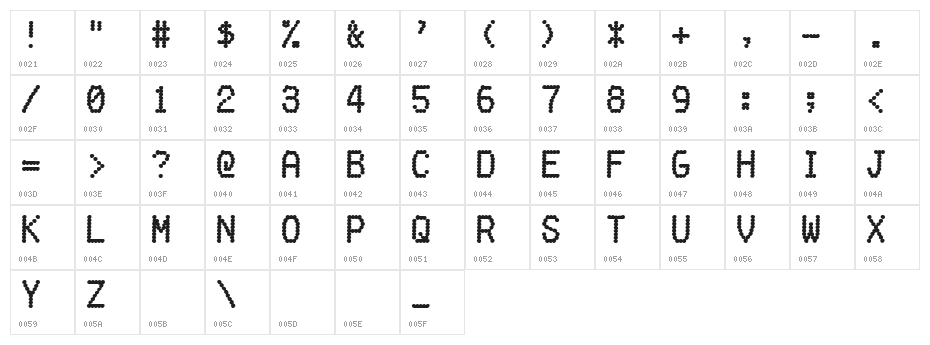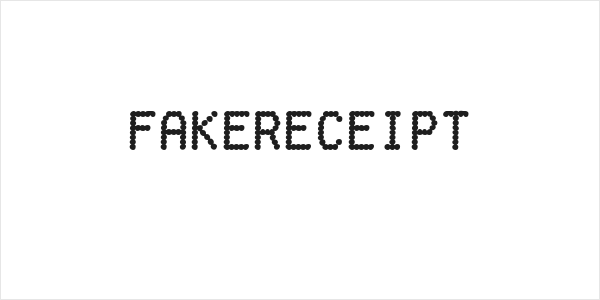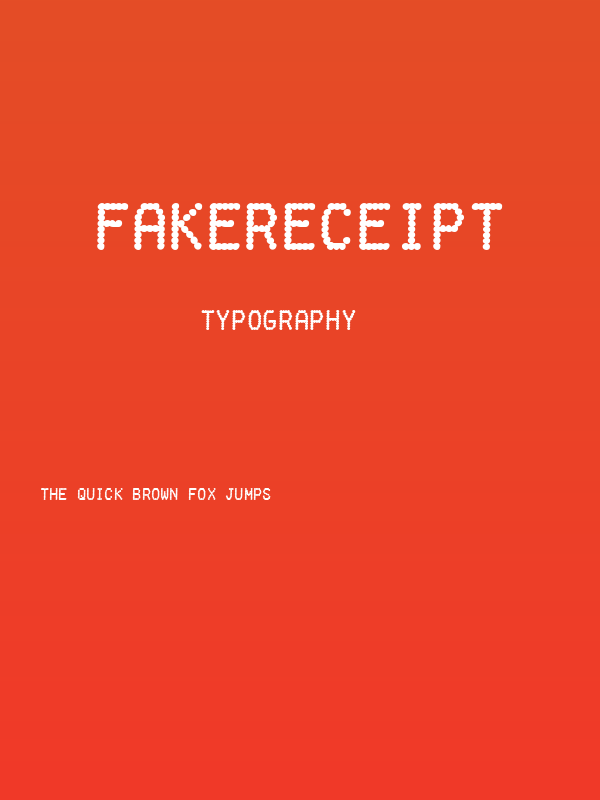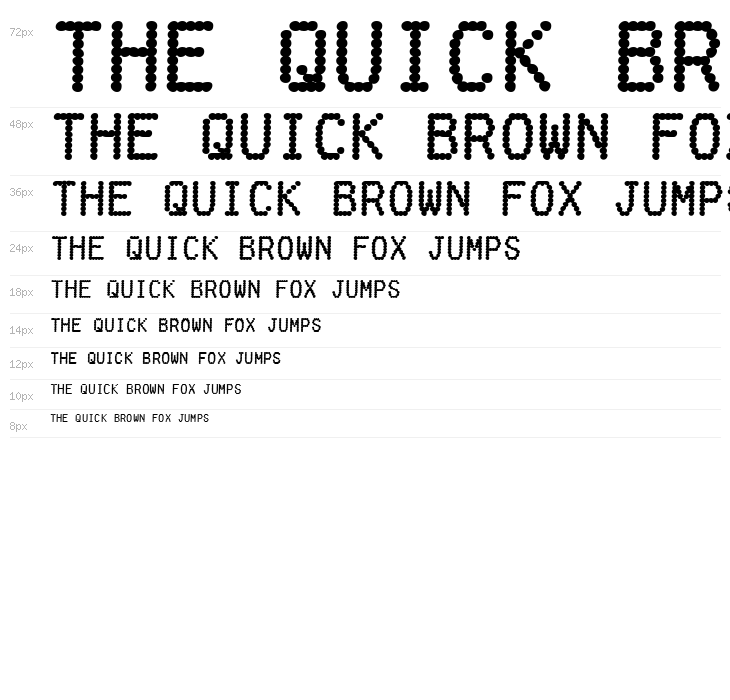
FakeReceipt Font
| Gesamtstil | Retro, Modern |
| Anwendungsfall | Logos, Posters, Digital Art |
| Vorgeschlagene Projekte | Ideal for retro-themed designs, tech-related branding, digital art projects, and creative posters. |